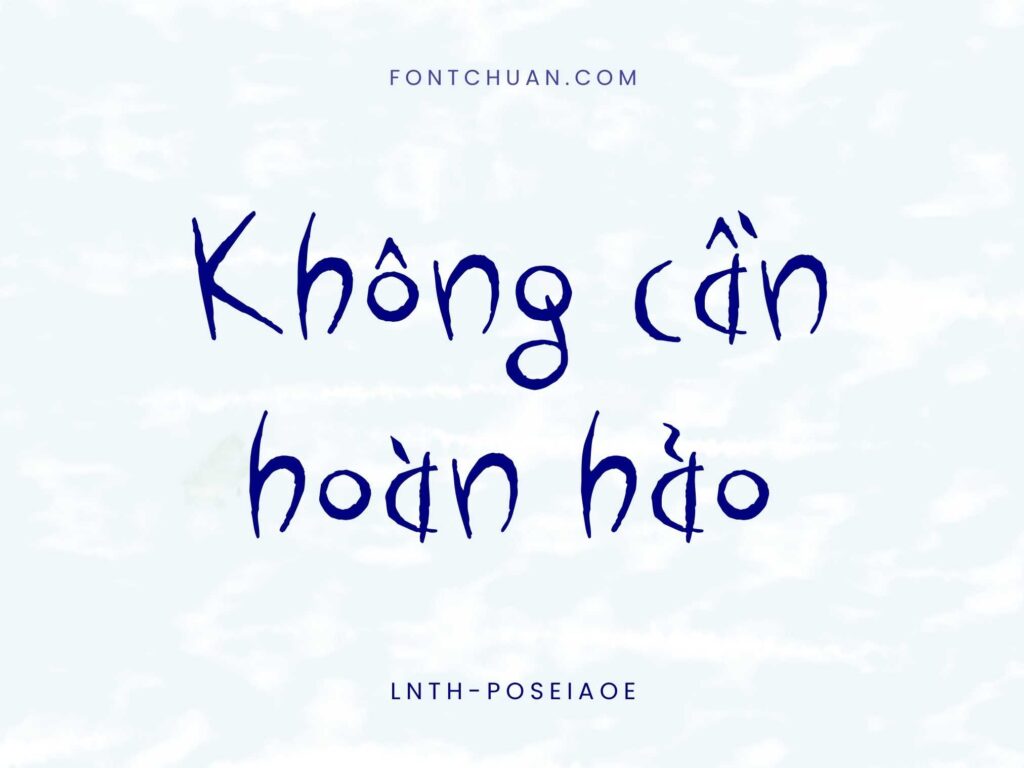
Font LNTH Poseidon Aoe Việt Hóa
Font Poseidon AOE là một kiểu chữ mang phong cách mạnh mẽ và cổ điển, lấy cảm hứng từ những nét chữ chạm khắc trên đá của nền văn minh Hy Lạp cổ đại. Với thiết kế chắc chắn, cấu trúc chữ vững vàng, font này tạo cảm giác uy quyền, trang trọng và phù hợp với các thiết kế mang yếu tố lịch sử, thần thoại hoặc branding cao cấp
Phiên bản này đã được Việt hóa bởi LNTH, hỗ trợ đầy đủ tiếng Việt cùng hơn 50 ngôn ngữ khác, giúp người dùng dễ dàng ứng dụng trong thiết kế quốc tế. Font Poseidon AOE được các thành viên Font Chuẩn sưu tầm và đăng tải nhằm mang đến một sự lựa chọn độc đáo, đặc biệt phù hợp với những dự án mang phong cách cổ điển và sang trọng
Về đặc điểm thiết kế, Poseidon AOE có các đường nét dày dặn, các góc cạnh rõ ràng, tạo nên một phong cách hoài cổ nhưng vẫn rất hiện đại. Kiểu chữ này rất phù hợp để sử dụng trong các thiết kế tiêu đề, logo, nhãn hiệu hoặc các ấn phẩm liên quan đến văn hóa và lịch sử
Font Poseidon AOE được ứng dụng rộng rãi trong các sự kiện như lễ hội, triển lãm nghệ thuật hoặc các thiết kế mang phong cách cổ điển. Nó phù hợp với nhiều ngành nghề như quảng cáo, bất động sản, công nghệ, giáo dục